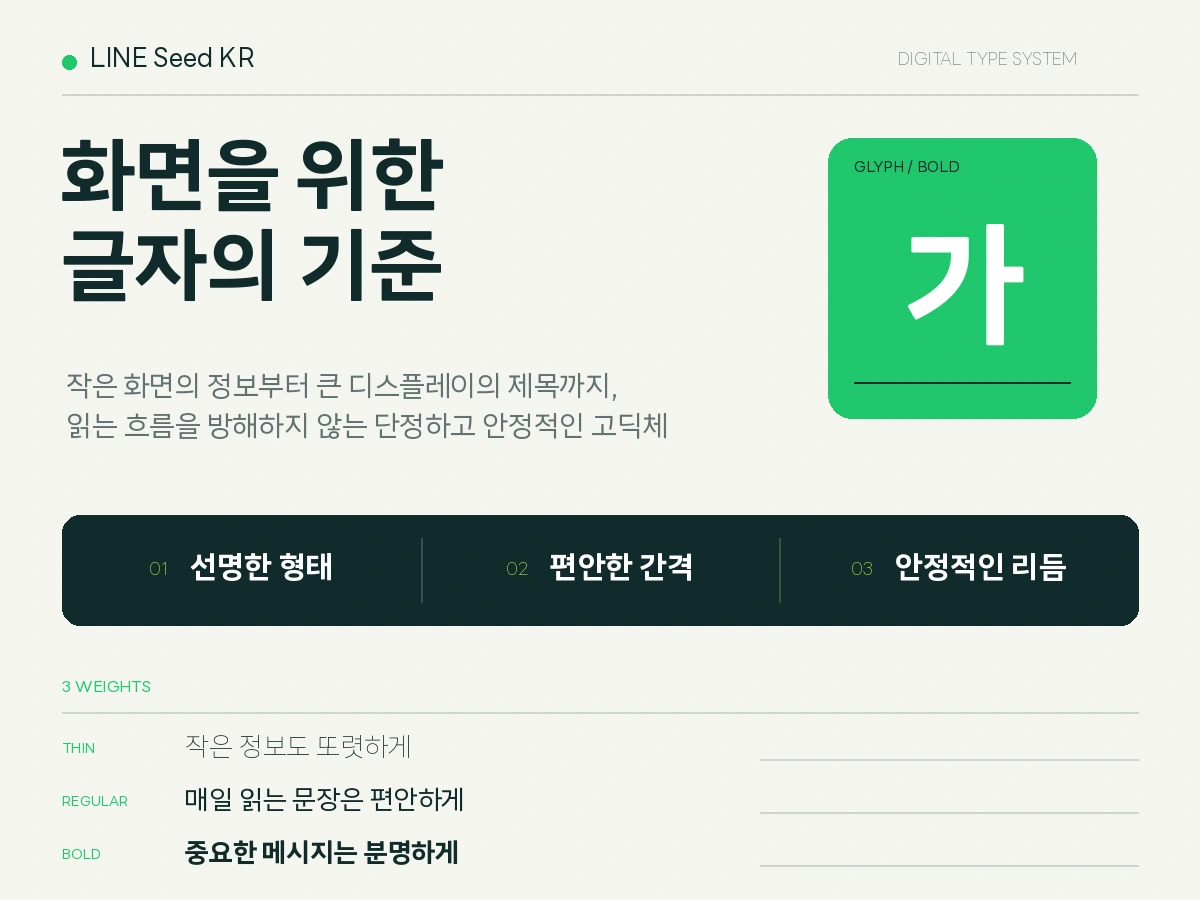
LINESeedKR — LINE에서 배포하는 무료 폰트입니다. 씨앗이 싹을 틔워 열매를 맺듯 함께 성장한다는 뜻을 담아, 화면 환경에 맞춘 본문용 고딕체
LINE이 자사 브랜드를 위해 만들어 무료로 푼 서체로, 한글은 산돌과 협업해 완성했습니다. 이름의 씨앗에는 뜻이 담겨 있습니다. 씨앗이 싹을 틔우고 열매를 맺는 것처럼 LINE의 서비스에 단단히 심어져 이용자와 함께 성장한다는 의미라고 밝히고 있습니다.
제작사가 설명하는 조형의 핵심은 두 가지입니다. 하나는 현대 한글 고딕에서 많이 보이는 네모꼴을 따르되 시각 중심을 가운데에 가깝게 두어 글줄이 안정적으로 흐르게 한 것이고, 다른 하나는 LINE 로고의 둥근 모서리를 글자와 숫자, 기호, 아이콘 전체에 공통 아이덴티티로 적용한 것입니다. 여기에 LINE의 여러 서비스를 아이콘으로 넣어 두어 타이핑하다 보면 뜻밖의 그림이 나오기도 합니다.
굵기는 Thin과 Regular, Bold 세 가지입니다. 오픈 폰트 라이선스로 배포되어 수정과 재배포가 자유롭고 폰트 파일 자체를 파는 것만 금지됩니다. 제작사는 상업적으로 쓸 때 출처를 함께 밝혀 주기를 권하고 있습니다.